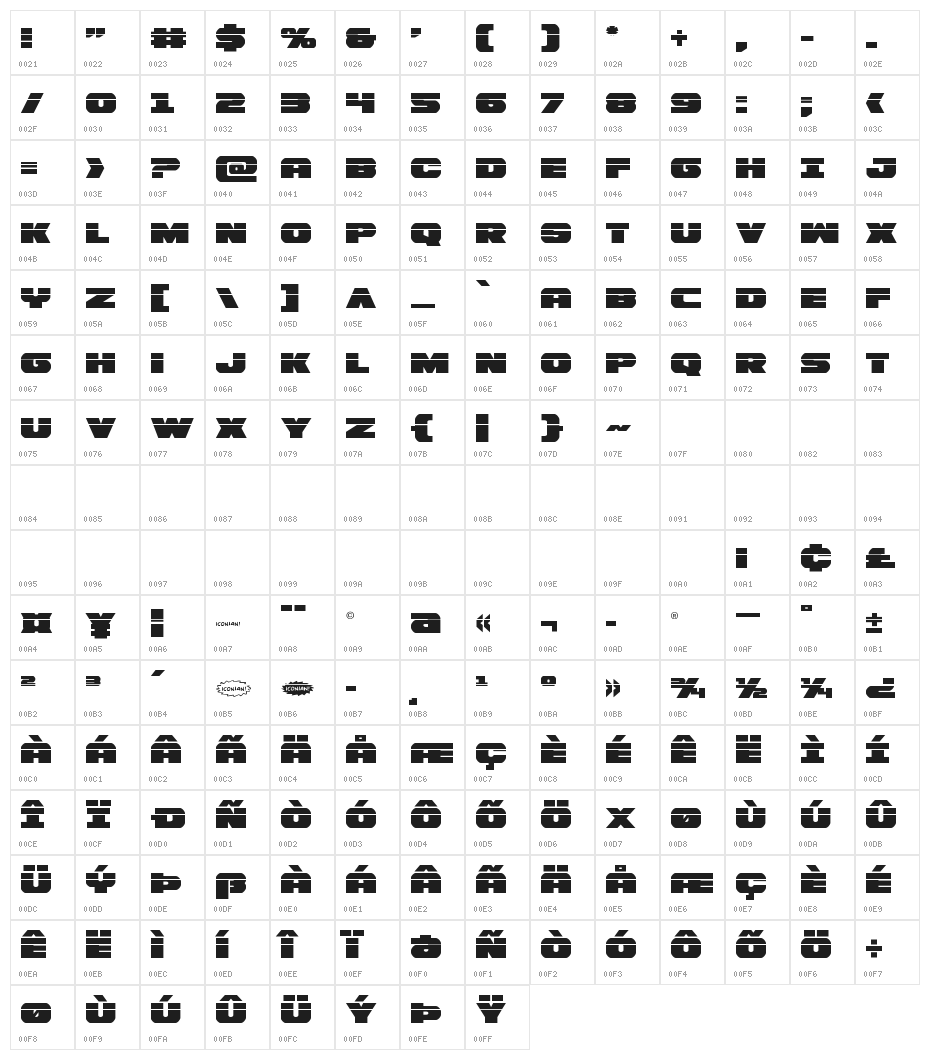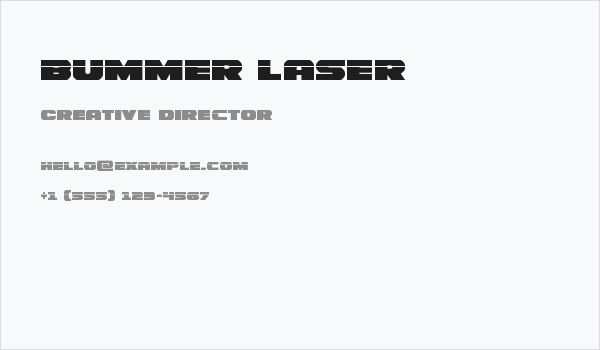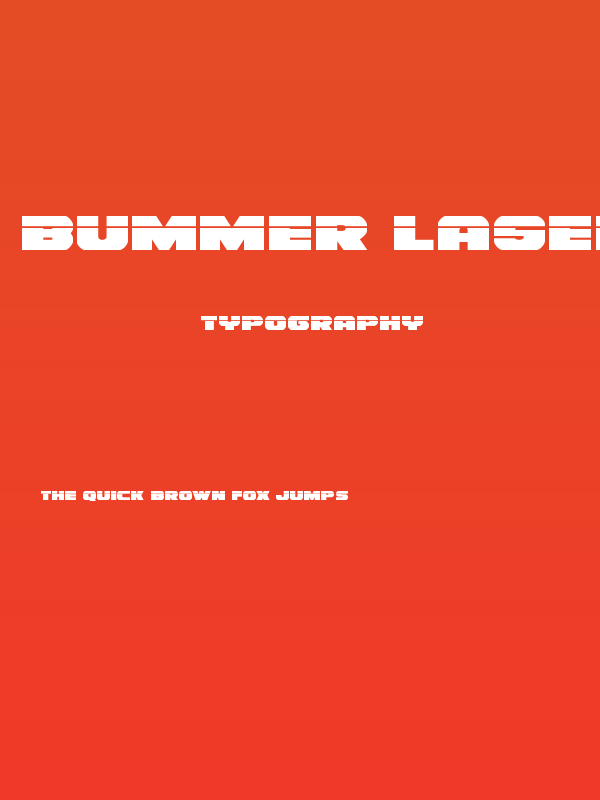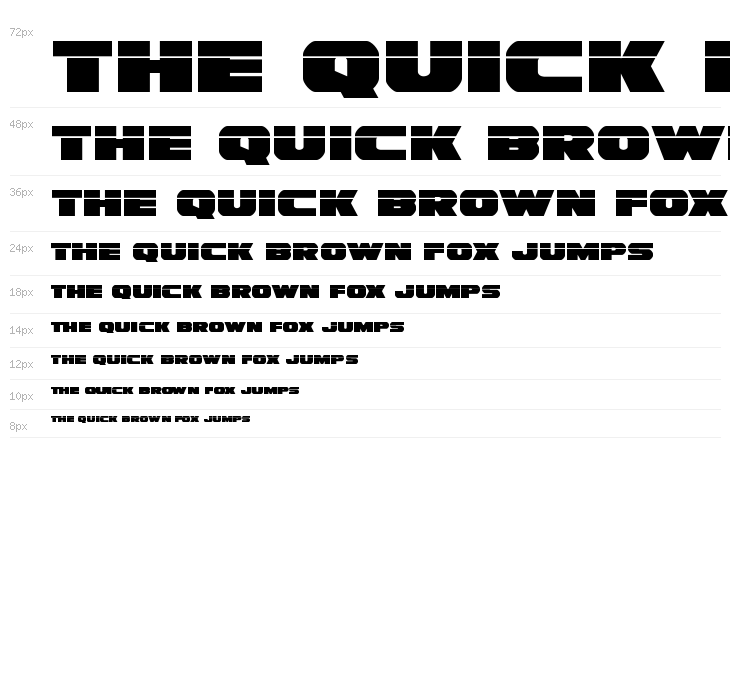
Bummer Laser Font
| Progetti proposti | Ideal for projects requiring a strong visual impact, such as posters, logos, video game graphics, and sci-fi themed designs. |